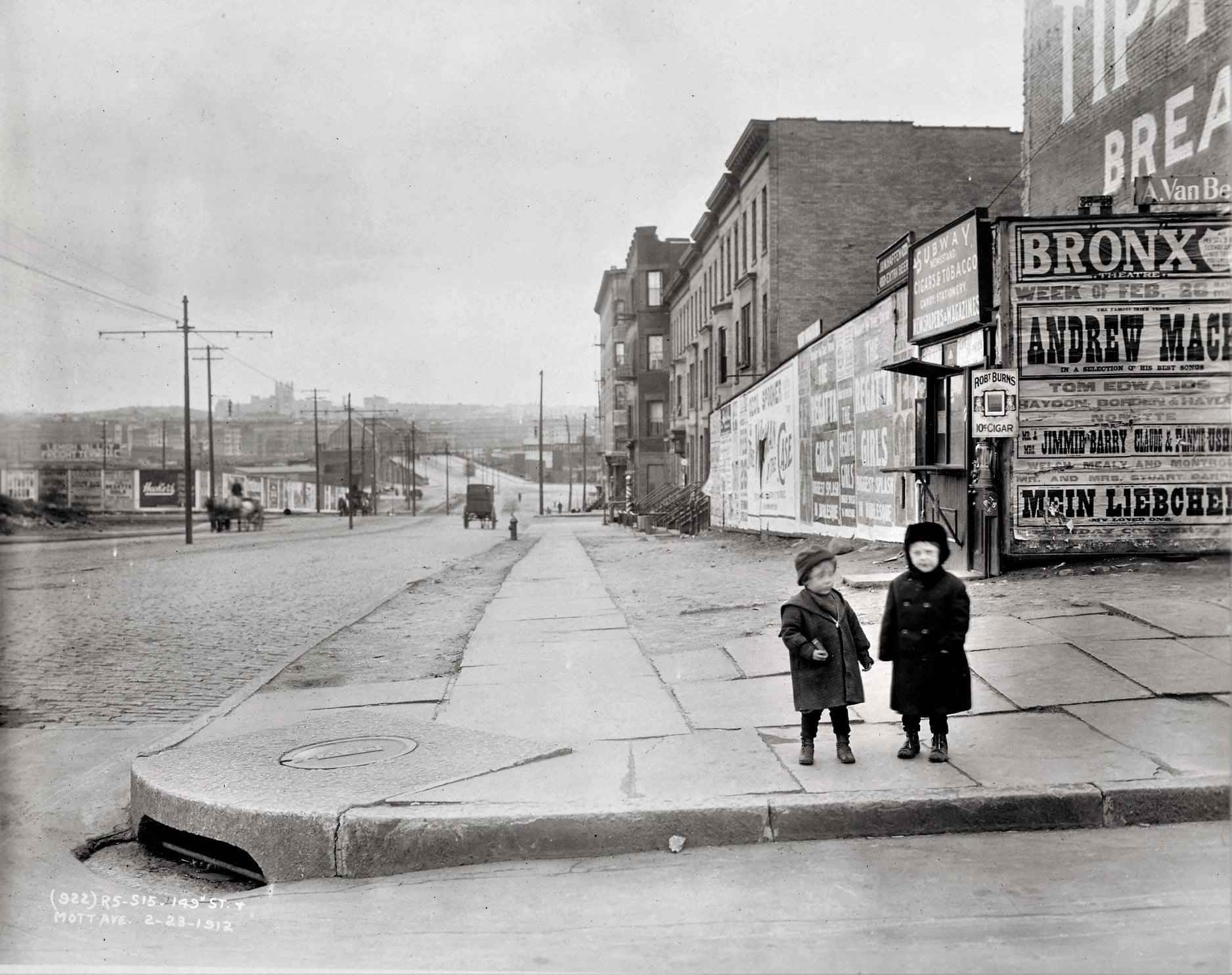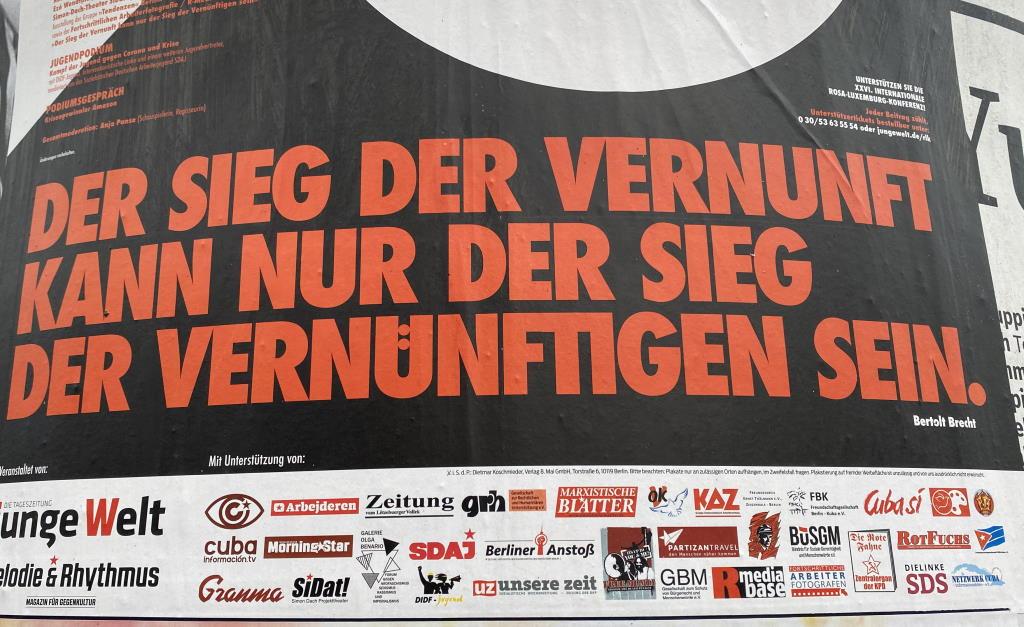
Wood type!
Auch damals schon mussten die Gesichter im Street view verwischt werden :-)
Was könnte denn "Mein Liebchen – New loved one" gewesen sein?
Hier wird ja ein Konzert beworben, also vielleicht Brahms' "Meerfahrt" (Mein Liebchen, wir saßen beisammen...)? Deutsch als Unterhaltungssprache war hier bis nach dem ersten Weltkrieg durchaus populär. Zu einer Mrs. Erhart habe ich leider nichts gefunden.
Habt Ihr gesehen, daß der Setzer sich bei "Liebchen" mit einer eins behelfen mußte?
Ich war davon ausgegangen, dass das ein Klebefehler ist und die rechte Plakathälfte die Serifen überdeckt. Das "v" direkt darunter sieht mir ebenfalls abgeschnitten aus.
Mich würde mal interessieren, wie eine Presse für solche Formate ausgesehen hat …
Ich schätze mal ne Nudel. DieAuflage war jawohl eher klein?
Tante Edith findet, dass ich vorschnell gepostet habe, denn es gibt da einige inhaltliche Schwächen. Der Autor scheint sich häufiger in den Begrifflichkeiten zu verlaufen und scheint nicht wirklich in den Standard reingeschaut zu haben.
Vielleicht nehme ich mir das auch nochmal als Typography.Guru-Video vor. Ist genau die Art von Wissen, die heute wichtig ist, aber in jedem neuen Typografie-Buch nicht vorkommt, weil es nicht zum »klassischen Wissen« gehört, das von einem Buch zum nächsten getragen wird.
Allerdings. Serifen sollen »kognitives Rauschen« fördern (A sans-serif font to reduce cognitive noise)? Wie geht das? Bleibt man da mit den Windungen des Gehirns wie mit den Maschen eines Wollpullovers an den Serifen hängen?
P.S.: Ich habe während des Studiums viel quergelesen (diagonal)  – mache ich heute nur noch, wenn der Krimi langweilig wird und ich vorankommen möchte. Denn ich finde es doch recht anstrengend, weil man ja die Peripherie sozusagen aktiv ins Geschehen miteinbezieht. Aber dabei lese ich keine Buchstaben, nur Wortbilder. Und das funktioniert am besten mit der am häufigsten trainierten Schrift; in meinem Fall (wie bei den meisten wohl) der Garamond.
Würde mich jetzt aber sehr wunder nehmen, ob das bei meiner Garamond-förmigen Serifenlosen Ysabeau auch ginge! 🤔
Ich bin grad zu faul zum Suchen, wir hatten mal einen Thread, in dem die Platzierung des Umlautanzeigers in der entsprechenden Versalie besprochen wurde. Deswegen poste ich das mal hier, ein wunderbares Beispiel linker Designkunst an einer Litfasssäule:
Zur "linken Designkunst":
Als ich anfing zu studieren, wurden die Mensen ständig von politischer Propaganda regelrecht geflutet. Die linken Gruppieren haben dabei, wie auch auf ihren Plakaten, eigentlich immer dadurch hervorgestanden, dass auf ihren Flugblättern jeglicher Weißraum vernichtet wurde. Als ob es zwischen den einzelnen linken Sekten einen Wettbewerb gab, wer mehr Buchstaben pro Quadratzentimeter Flyer unterbringen konnte. Es war eigentlich immer mehr Text auf so einem Zettel, als der deutsche Normstudentenmensch für seinen Normschiss braucht zum Lesen. Wo ich grad etwas in die Sanitärabteilung gerutscht bin, mir fällt gerade auf, dass es eine designästhetische Nähe zur Bildzeitungsoptik gibt! *staun*
Auch fällt mir jetzt in der Erinnerung auf, dass die Linken dabei keine echte Zielgruppe in ihrer Ästhetik ansprach. Die anderen hochschulpolitischen Gruppen hatten recht klar umrissene Zielgruppen und auch eine jeweils eigene Ästhetik. Die Mediziner-Liste (Liste ist sowas wie eine Partei, gemeint sind Wahllisten) zeigte freundlich lächelnde Menschen mit kurzen positiven Botschaften als Schlagzeilen, die Wirtschaftsfuzzis wurden mit fluffiger bonbonfarbener Wohlfühlästhetik bzw. angsterzeugende Sozialismuswarnungen angesprochen und die Conservativen (also zumindest in HH kam in bundestagsvergleich quasi rechts der SPD gleich die CSU).
Oh, das waren schon die Jungs von Ströer oder JCD, weiss nicht, wem die Litfasssäule gehört. Im Bahnhof (die Wände werden von Ströer betreut) waren jedenfalls auch welche bei gewesen.